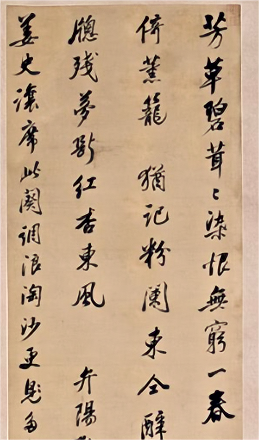
汉标沈荃行书浪淘沙词 By 真迹小字库 商用字体
字体全名: 汉标沈荃行书浪淘沙词
字体简介: 下载须知:本字库非标准GB2312字库。本字库只包含了沈荃《浪淘沙词》真迹上的“106个字”。此轴录“弁陽歗翁”浪淘沙词一首,计4行,行字不等。末款“充齋沈荃”。钤“沈荃印章”、“充齋”二印。无藏印。行书浪淘沙词》轴,清,沈荃书,绫本,纵178.2厘米,横44.3厘米。 此轴笔法流畅自如,布局疏宕,结字布白深得董其昌书法神韵,略参米芾险绝的结字体势,清劲秀雅,自具风神。